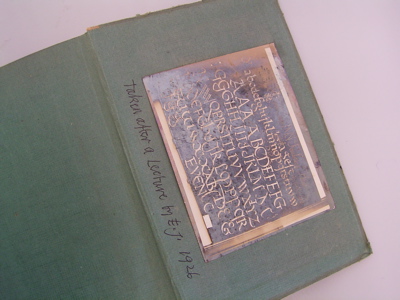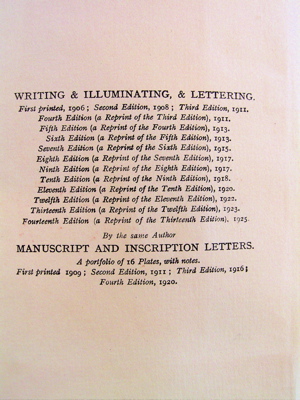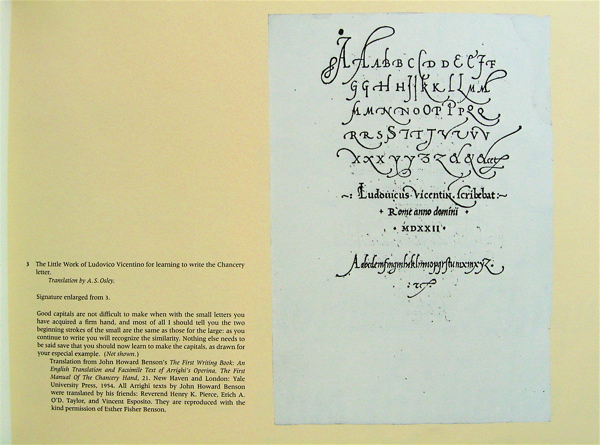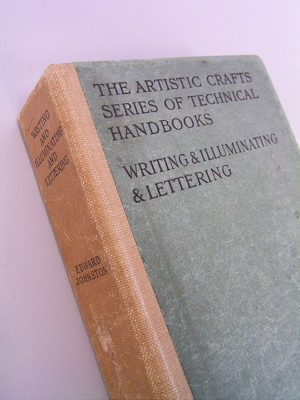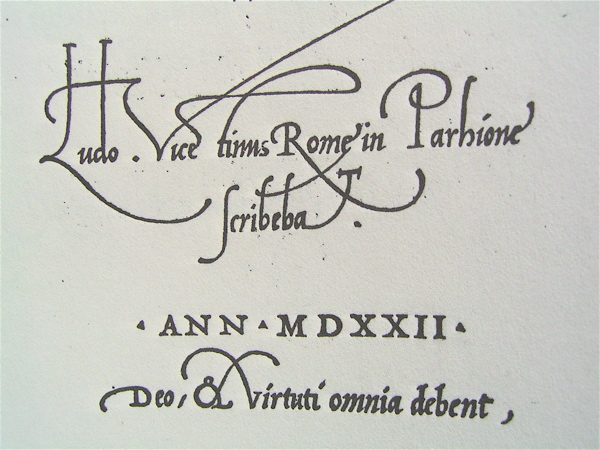
まだカリグラフィーが私の歴史の中に出てくるのは、このずっと先のことだったのに、文字を書いているこの表紙。今思うとなぜこのノートを選んだのかな、と不思議な気持ちです。
イギリス古寺巡礼―中世の美を尋ねる旅
夏に行ったイギリスの北部にも古い寺院が数多くあり、その歴史を教えてもらうと少しずつ中世のイギリスに触れる事ができて、もっといろいろ知りたいと思う様になりました。
今年の4月に出版された芸術新潮では、イギリスの古寺巡礼と題して、中世の美を尋ねる旅を特集しています。芸術新潮 2007年 04月号 [雑誌]
特に11世紀半ば〜12世紀のロマネスク時代にスポットを当てています。
ロマネスクという名前は、ローマ風のという意味ですが、当初は「古代ローマには及ばない粗野なローマ風の様式」という蔑称としての側面が強かったそうですが、現在では、このイギリスのロマネスク時代は、ケルト、ローマ、アングロ・サクソン、ヴァイキング、ノルマン、など多くの民族の文化がまじりあった魅力ある文化の時代としてとらえています。主に中世後期のゴシックと分けて考えているのだそうです。
だから、修道院の廃墟や村の小さな教会のドアや柱や地下室などに、その面白い美術は潜んでいるのだそうです。
今年の夏に尋ねたノースイーストにあるダーラム大寺院も、この本にはちゃんと載っていました。この寺院もロマネスク様式だということなので、行く前にこの本に出会っていたら、きっともっと楽しめたかもしれません・・・(^^;)
カリグラフィーのシンポジウムのあったサンダーランド大学のすぐ裏にも、St.Peter's churchというとても古い教会がありました。
そこは、674年にBenedict Biscop によって建てられました。ここには1300年以上も前に作られた当時のドアがまだ残っています。しかも、そこを通ったり触ったりが出来るのですよ!
Wearmouth-Jarrow Abbey
St. Benedict Biscop,
Bede
The Codex Amiatinus などなど。
歴史的にまだまだみどころや興味深いストーリーがたくさんあるので、次回行くときには、予習をして行きましょう。
ジョンストンの本
さて、イギリスのサンダーランドのインターナショナル・カリグラフィー・シンポジウムに参加しているmojitor-sからの特派員報告です。
なかなかインターネットにつなげる場所がなく、ご報告できませんでしたが、ようやく環境が完備された場所に来ることができたので、少しでもこちらの生の様子がお伝えできれば!
この本のタイトルをよ〜〜〜くご覧下さいまし!
これはそうあのカリグラフィーのバイブルとも言われている「Writing Illuminating and Lettering」です。著者はエドワードジョンストンです。遠山由美さん翻訳でも出版されています。
書字法・装飾法・文字造形
みなさんが持っているのと違う表紙です。
それもそのはず、これが出版されたのは1920年代。ジョンストンが亡くなったのは1944年ですから、まだ彼がいた頃のもの。第14版です。
良い本はず〜っと長く出版されますが、今はこの本は第何版までいっているのでしょう。優れた本はなが〜くなが〜く愛され役に立つのですね。
みなさんの手元にあるこの本をちょこっと開いて見て下さい。第何版になっているでしょう。
カリグラファーの顔
このお方、カリグラフィーや活字を学んでいる方なら多分誰でもご存知のエドワードジョンストンです。
羽ペンを持って姿勢よく傾斜板で書いていますね。左手にはちゃんとペンナイフかなにかを持って、紙を押さえながら書いています。
こんなにきちんとした格好で書いていたのかしらん??
ネクタイしたスーツ姿ですよ!
昔のカリグラファーの姿は余り残されていませんが、有名なのは15世紀のジャンミエロさん。
彼の姿を書いた絵は2点だけ残っているそうですよ。
詳しくは高宮利行先生著の「本と人の歴史事典」に詳しく載っています。
ジョンストンさんは写真だから間違いはないでしょうが、肖像となるとまったく違う人だったということもありえるのかもしれません。
さて、肖像と言ったら、やっぱり好きなのはコレ!
以前mojitor-hさんやmojitor-tさんとスイスのサンクトガレン修道院の図書館に写本を見に行ったときに、ちょうどアルクィンの没1200年の記念シンポジウムのよう学会が開かれていました。そのパンフに載っていたアルちゃんの顔。
味がある良い顔してますよね。賢そう。
アルクィンはイギリスのヨーク出身の修道士でしたが,フランク王国のカール大帝(シャルルマーニュ)が招いてフランスのトゥールで、学者として活躍したのです。
カロリングルネッサンスにおける文化運動では重要な役割を果たし、あのカロリンジャンの書体を生み出したと言われています。彼が実際に書いたかどうかはわからない、と以前取った歴史のクラスでは教わりましたが、実際はどうだったんでしょうねぇ。
有木さんの書
京都の壬生寺に行ったときに、そこにあった書を見ていたら、偶然その書を書いた人の子孫と言う方に出会いました!なんというラッキー!
有木さんとおっしゃって、驚いた事にどう見ても外人さん。(日本語は達者・・というより日本人そのものでした)
ご先祖さまはイタリアからだそうで、昔ルネサンスの時代にはやはり書家として活躍していたそうなのです。と言う事は代々書家の家系ということです。
この遠くを歩いていらっしゃるのが有木さん。
ご先祖様が書き残したものは貴重な写本として残されている、とおっしゃるので、アレ待てよ!?有木さん??アリギさん?アッリギさん?・・・・もしかして あのArrighiさん?
え〜っ!!!!なんということでしょう!Arrighiとはルネサンス時代の非常に有名な書家なので、イタリック体の教本なども出版したライティングマスターの神様みたいな人なのです。
もちろん教室にも彼も書いた物が載っている本はありますよぉ〜!
それを伝えたら、有木さんとても喜んでくれました。そうですよね、こんな京都で偶然ご先祖様をよく知っている人に出会えるなんて。わ〜ん。すご〜い!
きっとライティングマスターの神様が出会わせてくれたんですね。ありがとう・・・・
ヨーロッパ中世の修道院文化
みなさま、ゴールデンウィーク後半、いかがお過ごしでしょうか。東京は見事な五月晴れで、家の中にいるのはもったいない1日です。
しかし、こんな日だからこそ、はるか昔ヨーロッパ中世の時代にさかのぼって、静かにスクリプトーラム(写字室)で写本を書いていた写字生たちに思いを寄せるのもいいかもしれません。
NHKラジオ第2放送カルチャーアワー、歴史再発見という番組で、現在中央大学文学部教授杉崎泰一郎先生による「ヨーロッパ中世の修道院文化」が放送されています。第1回目は4月に始まっていて、ちょうど今日は5回目の再放送の日です。
全26回なので9月の最終週までのシリーズです。ヨーロッパの文化や歴史を深く理解するために、中世の修道院の世界に目を向けることが歴史の再発見につながる、という内容になっています。
中でも第7回は、みなさん必ず聞きましょう!「写本の作成」というタイトルですよ〜。
ヨーロッパ中世の修道院文化